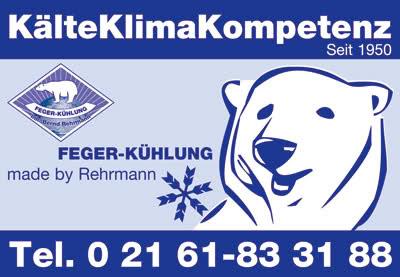
Suche wieder mal eine Schrift:
Ich bi auf der Suche nach der Schrift auf diesem Bild:
Die Firma weiß es leider nicht merh und ich brauche für die Webseite diese...
OK, die konnte ich nicht 100% nachschauen, da meine hier ohne Umlaute ist...
Bei meiner Helvetica wurden die Umlaute nicht dargstellt...keine Ahnung warum...jetzt funzt es plötzlich. Daher konnte ich das "ä" nicht kontrolieren...also bei meinen Fonts vergleichen welche das sein könnte...
Und in der Regel sehen die Punkte auf den Umlauten dem i-Punkt sehr ähnlich,
da kann man sich ganz gut an die Schrift ranpirschen. :)
Es ist fast exakt die Helv. Neue 95 Black
Erklär dem Kunden, dass es die 1950 noch garnicht gab und gut iss :?